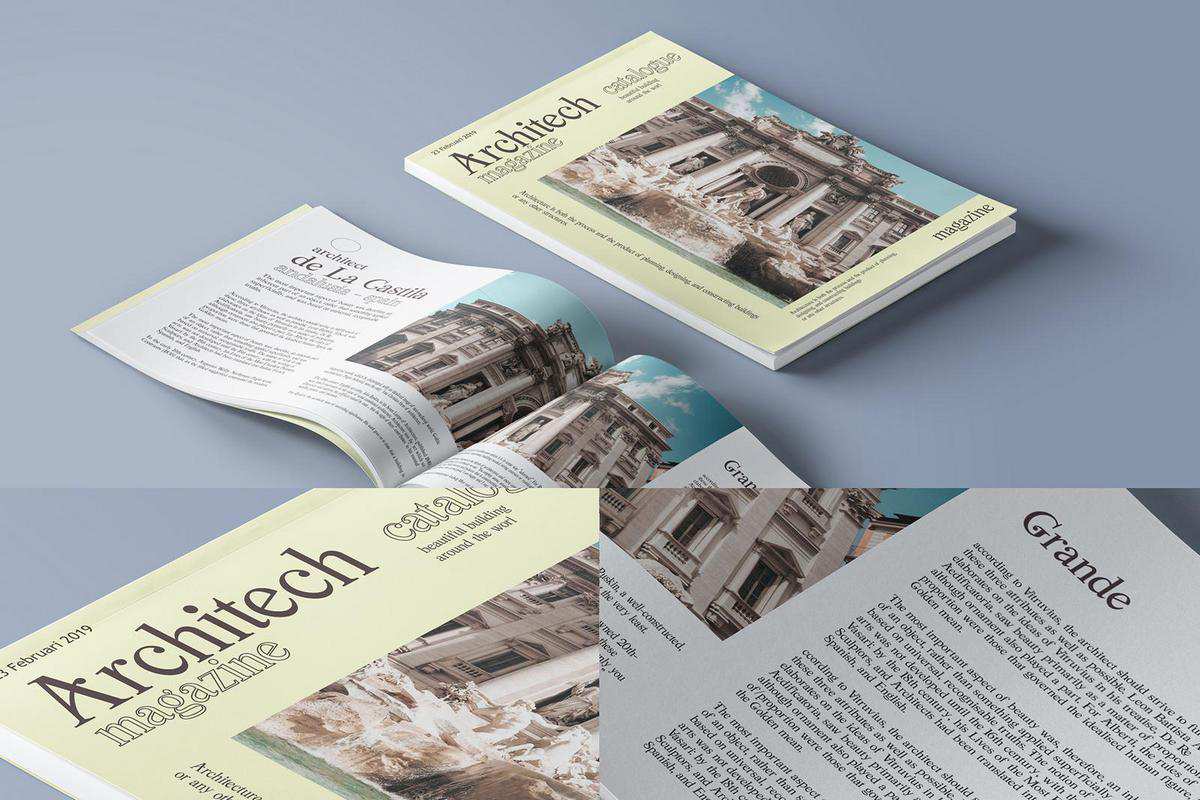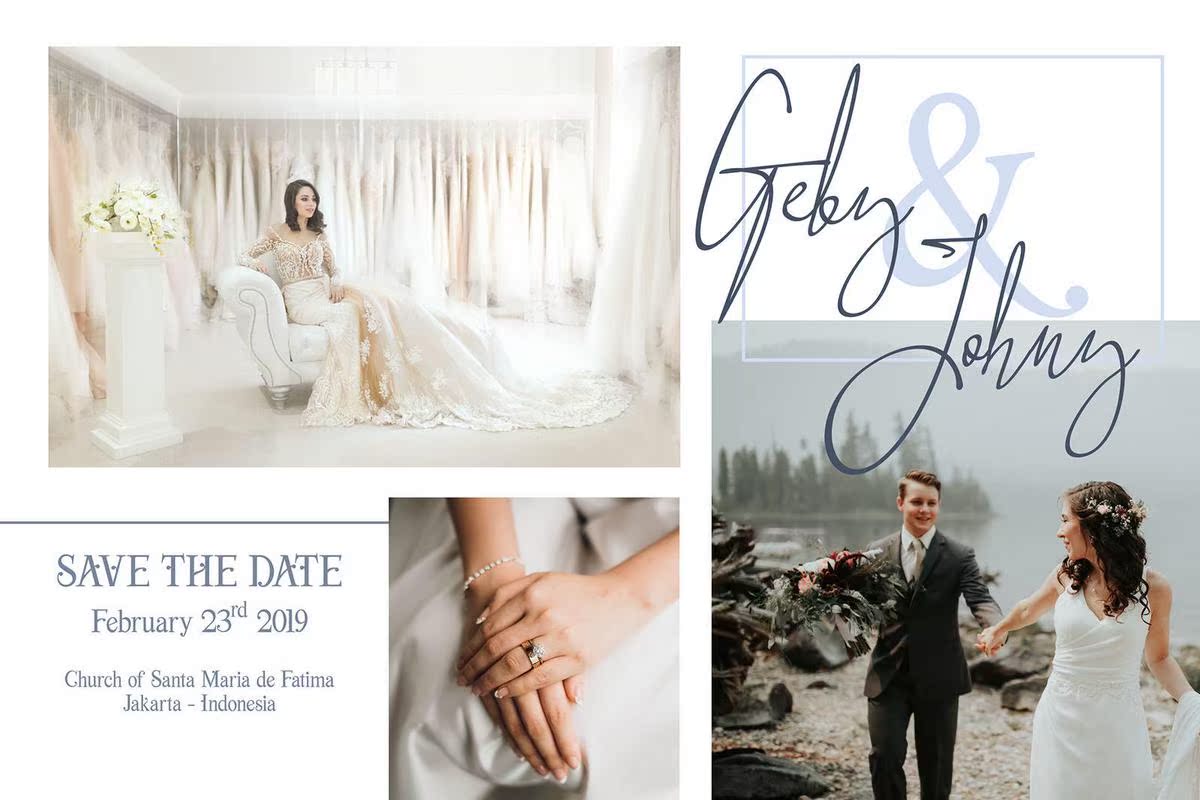
Viktoria IseautifulClassicFontduothatsforgorgeousquotes、logo、海报、网站、婚礼庆典、书籍、社交媒体等等!Viktoria IseautifulClassicFontduothatsforgorgeousquotes、logo、海报、网站、婚礼庆典、书籍、社交媒体等等!